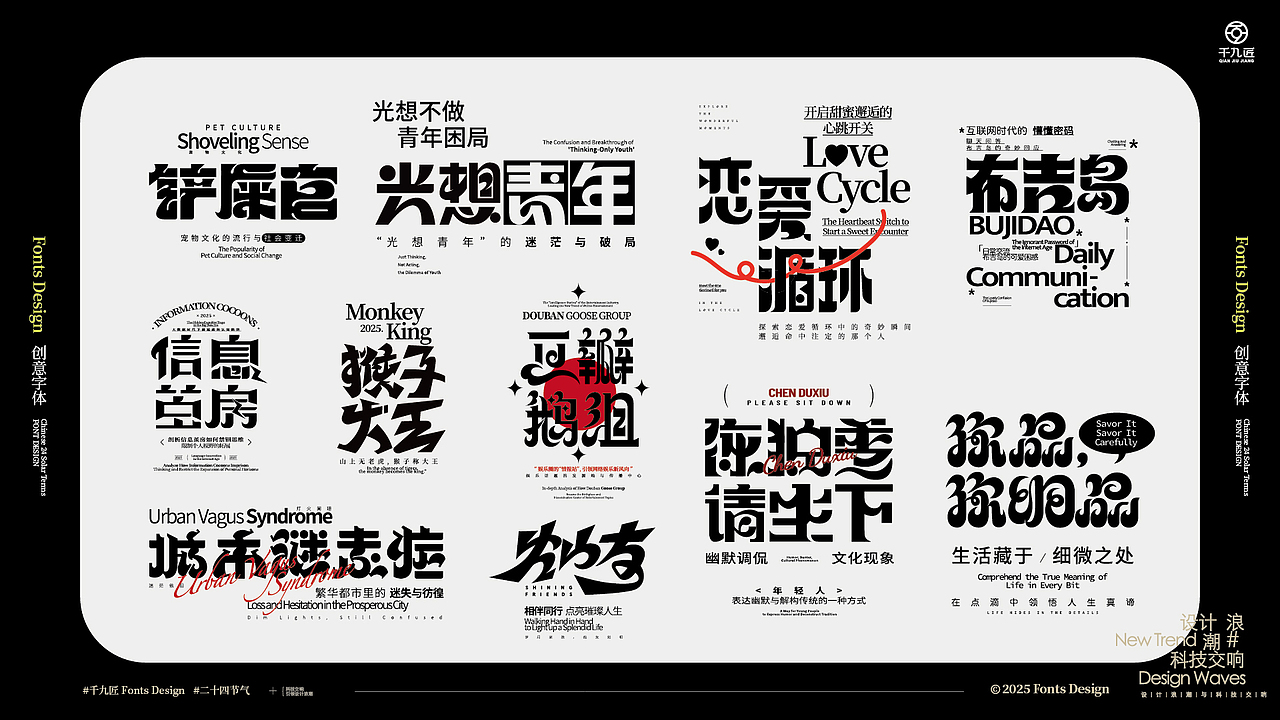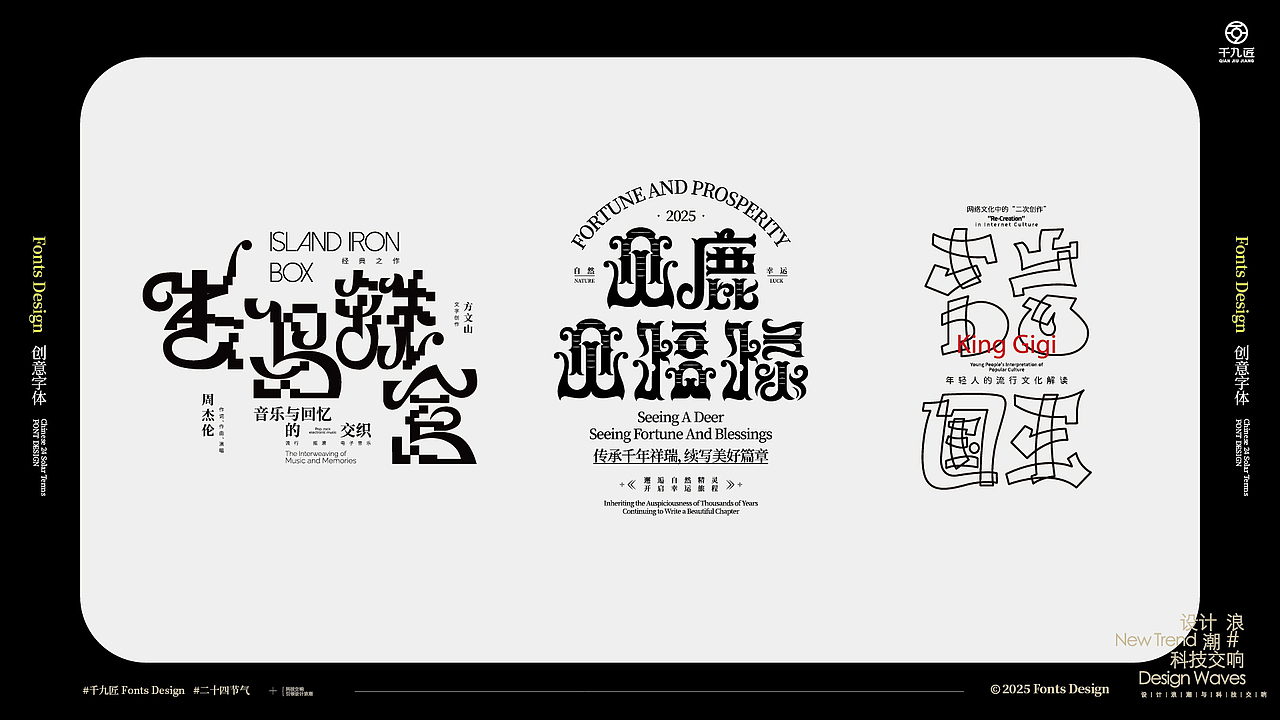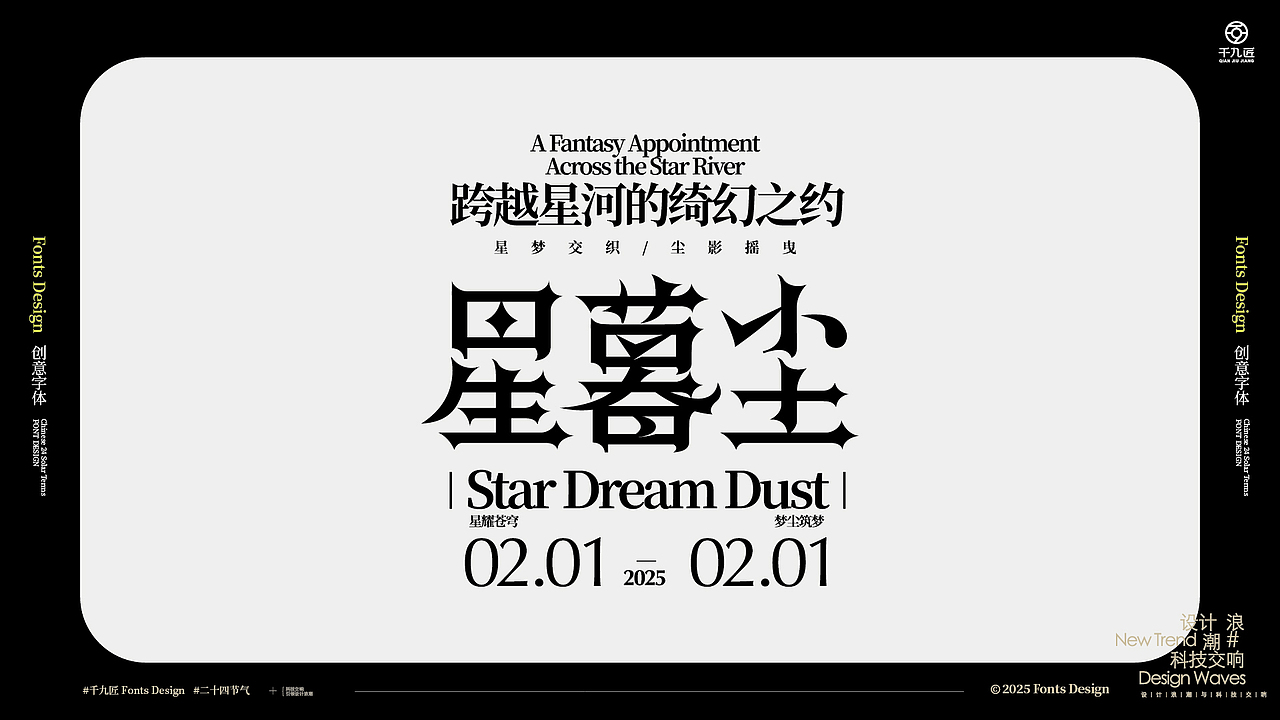
创意字体设计:文字的无限可能
在当今视觉设计领域,创意字体设计正以其独特的魅力和无限的创意,成为吸引观众眼球、传递情感和塑造品牌形象的重要工具。这组创意字体设计作品,以独特的视角和创新的手法,重新诠释了文字的美学与功能,展现了文字在视觉艺术中的无限可能。
突破传统,重塑文字的边界
在创意字体设计中,我们不再满足于传统的排版规则和字体样式,而是大胆突破,重新定义文字的边界。每一个字母、每一个笔画都被视为独立的艺术元素,通过巧妙的变形、重组和创意的排版,赋予文字全新的生命力。无论是将文字与图形结合,还是通过独特的笔画设计,我们力求让文字在视觉上更具吸引力和表现力。
融合多元风格,展现独特个性
这组创意字体设计作品融合了多种风格,从简洁现代到复古华丽,从手绘风格到科技感十足的未来主义,每一种风格都经过精心设计,以适应不同的应用场景和传达不同的情感。复古风格的字体通过模仿历史时期的排版和字体样式,唤起怀旧情感;而未来主义风格的字体则通过简洁的线条和几何形状,展现出科技感和现代感。手绘风格的字体则通过不完美的笔触和自然元素,展现出亲和力和趣味性。